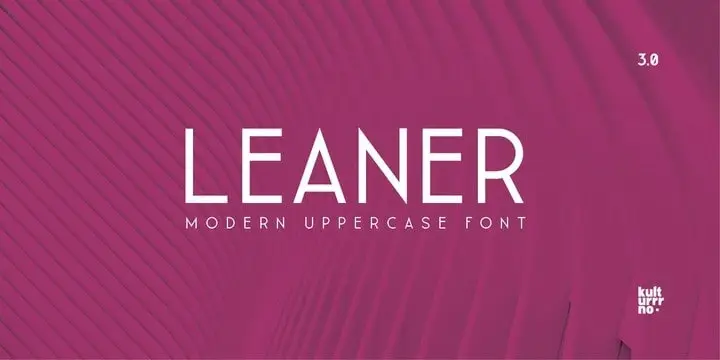
A Leaner Sans Serif é uma elegante família de tipo geometricamente simples e com traços afiados. Reduzida a suas características essenciais, ela oferece um design amigável que vai desde seus caracteres excentricos até o seu conteúdo mais convencional. Seja para headlines ou subtítulos, esta fonte irá sempre dar um toque de dignidade à sua criação enquanto manter-se altamente legível. A Leaner é ideal tanto para aplicação em logotipos e nomes comerciais quanto para escrever rótulos modernos de filmes. Seja qual seja a função da sua arte, esta fonte irá ajudar você a destacar seu trabalho no mercado competitivo do design gráfico brasileiro.